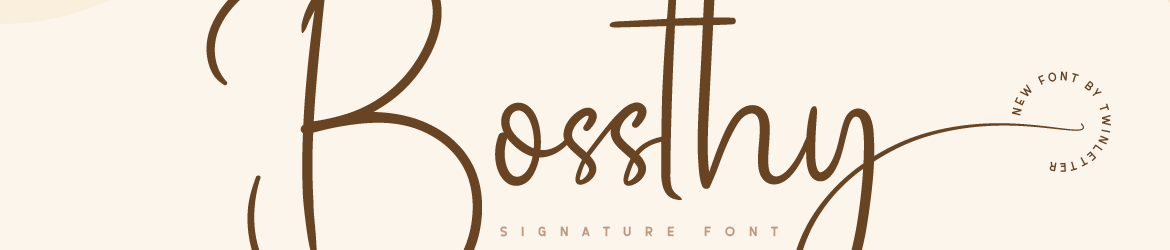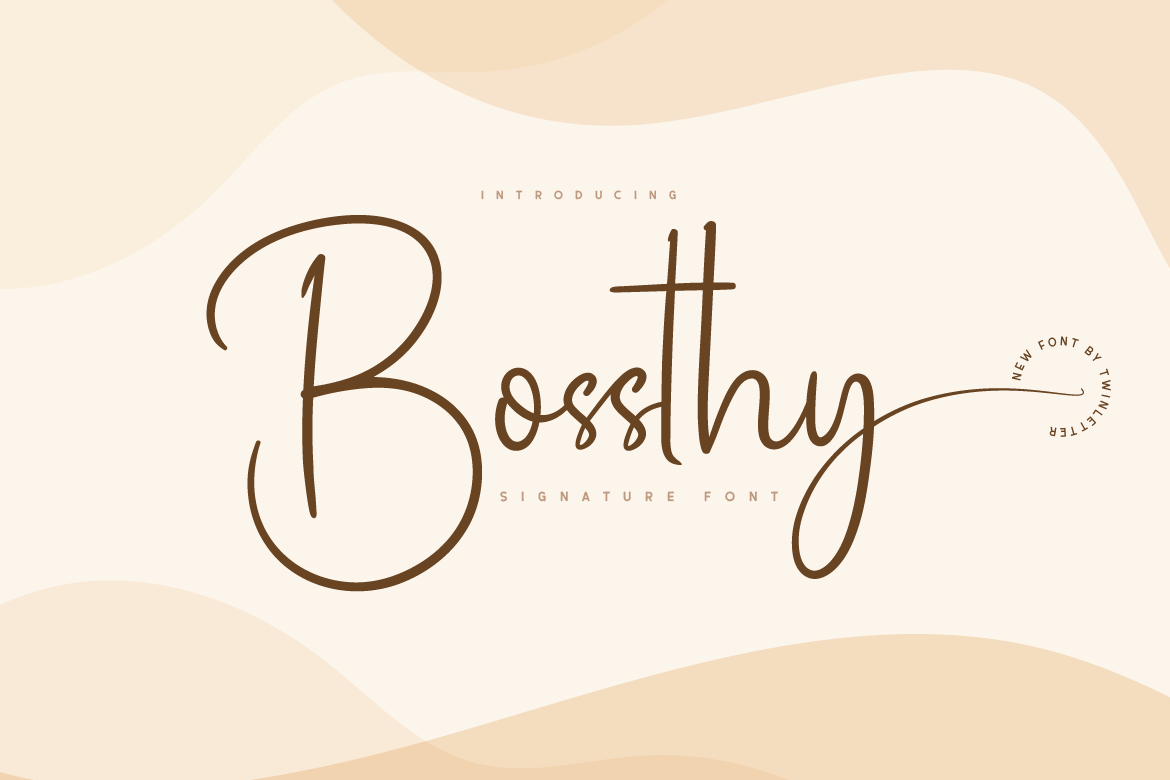
Bossthy Font – Fonte Grátis
Bossthy Font
A Bossthy Font é uma elegante tipografia script que transmite delicadeza com sua linha fina e suave, perfeita para quem busca uma fonte sofisticada para trabalhos de arte digital ou design gráfico. Este PUA (Unicode Private Use Area) encode permite que você faça uso fácil dos vários símbolos e detalhes ornamentais da fonte, criando designs incríveis que capturam a essência desta tipografia única. A Bossthy é perfeita para designers buscando um acabamento sofisticado em suas criações digitais. Ela traz uma nova dimensão ao design de textos e interfaces gráficas, tornando-a indispensável para quem busca experimentar algo novo no mundo da tipografia.